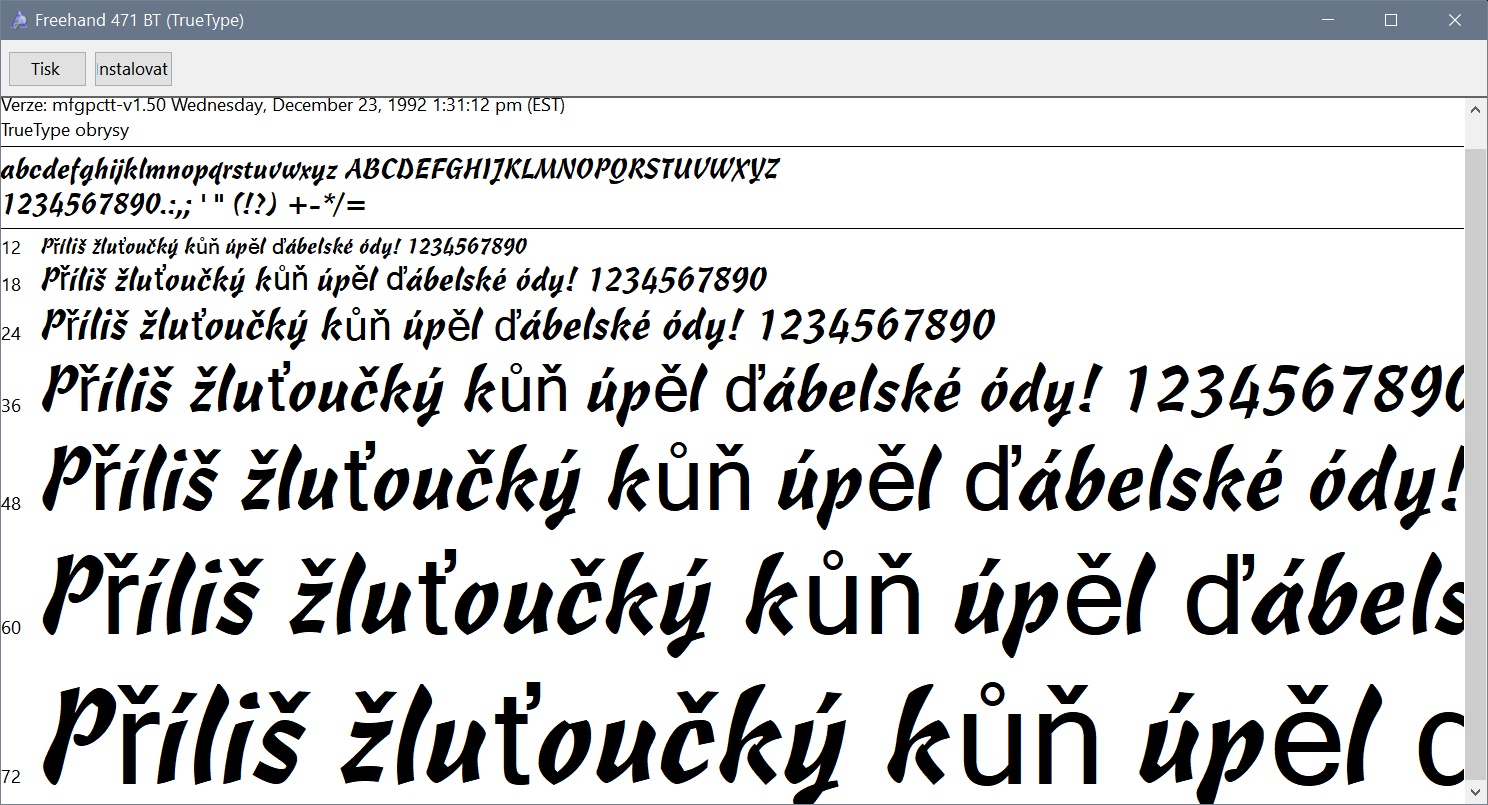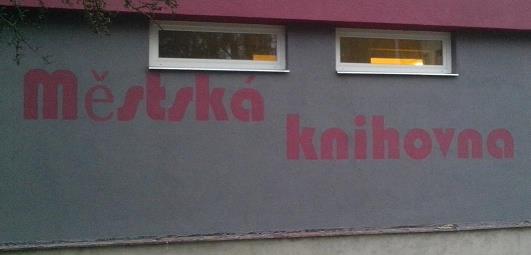
Neexistuje na trhu, ale ak chceš skriptové fonty s úplnou CZ/SK diakritikou, hľadaj na nete súbory písma:
Snáď si niečo vyberieš, ak chceš napodobniť v MS Word rukou písané údaje, koncepty svojho profesora/učáka/dochtora.
celý text tím napsat nepůjde, ale nadpis možná jo.
používá znaky nad 238. řešil by to open-type font, ale když má starý ttf, musí si pomoct.
Tohle vypadá skoro česky:
Na první pohled to české není.
Takže skoro česky to není. Co takhle angličtina s diakritikou?
Angličtina diakritiku nemá. Na obrázku jsou dva fonty, Freehand a nějaký Arial...
Je to tak, písmena s čárkou, háčkem jsou nahrazena jiným typem písma... Děkuji všem za odpovědi.
- ne všechna, jen některá písmena s diakritikou nejsou definována. pak jsou ve windows nahrazena něčím z výchozí rodiny znaků.
- bez substituce národní stránky pro ttf windows nejspíš nevidí ani tu diakritiku, kterou font obsahuje.
co vlastně funguje jde ověřit třeba ve wordu:
Když se příliš žluťoučký kůň nahradí příšerně žluťoučkým, jsou tam všechna česká písmena. Někdy se hodí i slovenská (tj. navíc ŕ ĺ ľ ä ô to je snad všechno), na to žádnou básničku neznám.
Jasná Staroslověnština. Ani nevíš, co odmítáš.
Prý je to městská knihovna v Týništi nad orlicí.
Evidentně to dělal někdo s IQ 37. :)
Ne ne, dělal jsem to sám.
Kdybych to viděl, beru ě v jiném fontu jako umělecký záměr. Jinak jsem podobné problémy řešil, když jsem potřeboval nějaké písmo, co mělo vypadat nějak, tak jsem české znaky nahrazoval jiným podobným písmem, které nevypadalo v tom nápisu jako pěst na oko. Mýval jsem svého času slušnou sbírku fontů, všechno, co se tehdy dalo stáhnout, že jsem narazil na limit winsows, který kupodivu nebyl 1024 (i když to tak vypadalo, někde u tisícovky se to zarazilo) ale 65k znaků seznamu fontů v registru.
V dávných dobách pamatuju, že existoval program na úpravu ttf fontů, kde se daly ty znaménka dokreslit (co si pamatuju dalo to fušku, aby to nějak vypadalo a pak aby windows 95 to upravené písmo přijmul, tak jsem to udělal jen jednou a pak na vše zapomněl). Od té doby jsem se o to nezajímal (opravdu nemám náladu kreslit si písmenka), ale předpokládám, že v dnešní době zavirovaných fontů a nutnosti jejich podpisů to bude daleko složitější.
Nějaký program na tu úpravu .ttf jsem kdysi taky použil (v XP nebo W7).
Tehdy nebylo tolik českých fontů písem a tak jsem pro jedny stránky tu diakritiku dodělal.
Nebylo to ani moc složité. Ale je to dávno, o weby se už nepokouším, nechávám to mladším a krásnějším